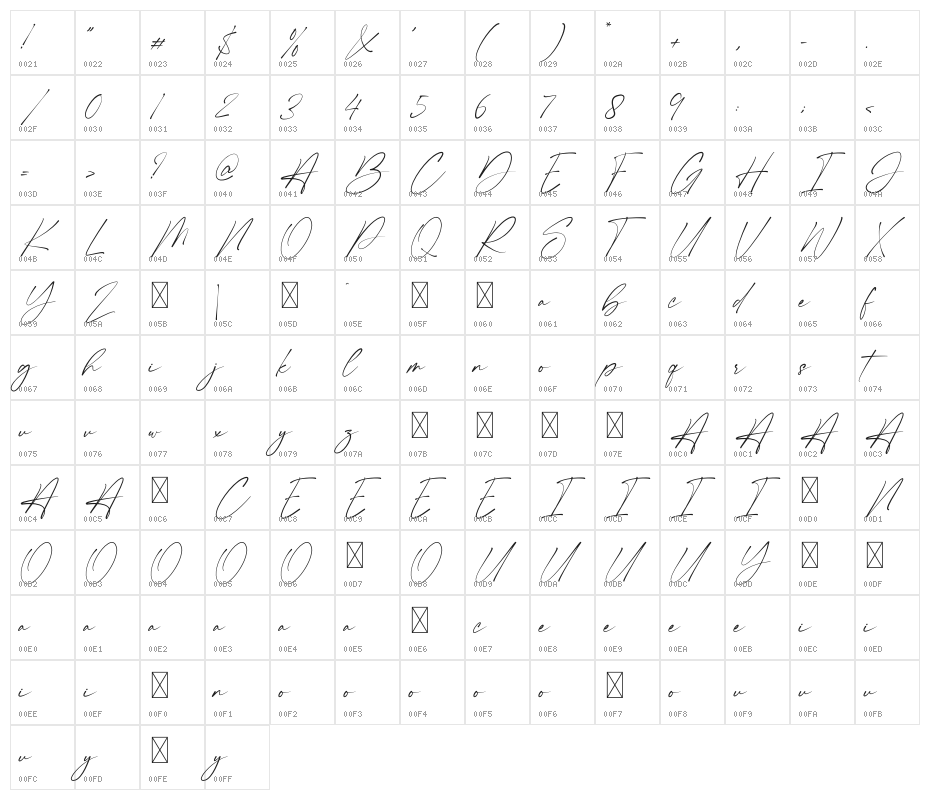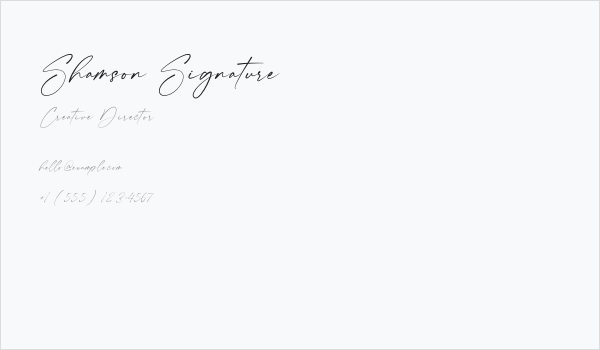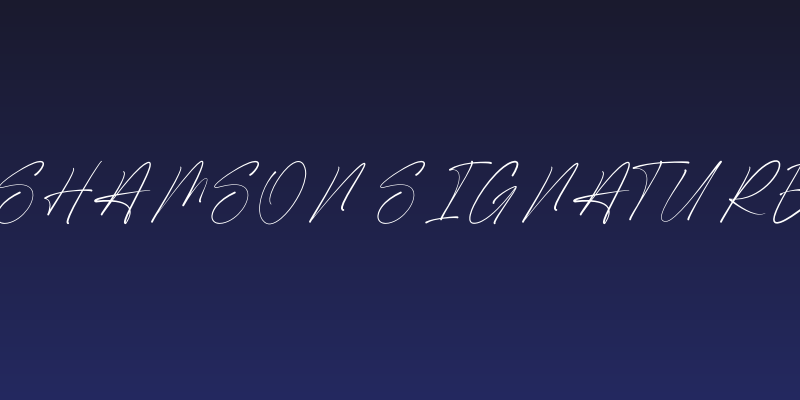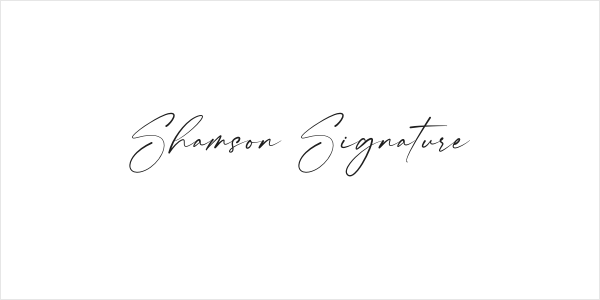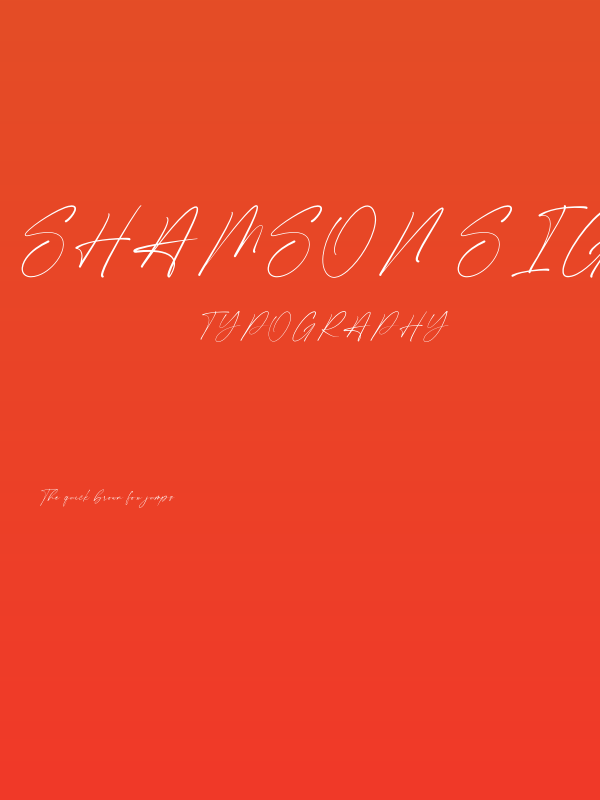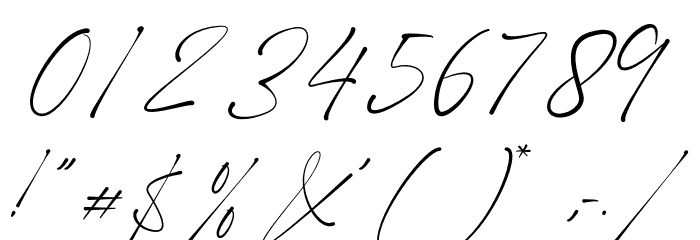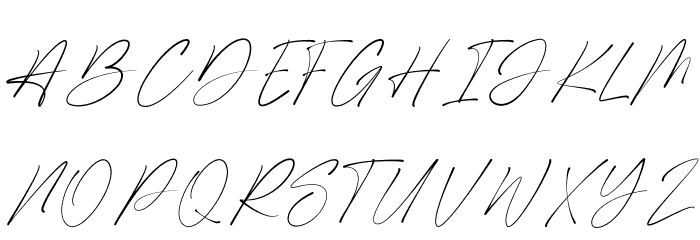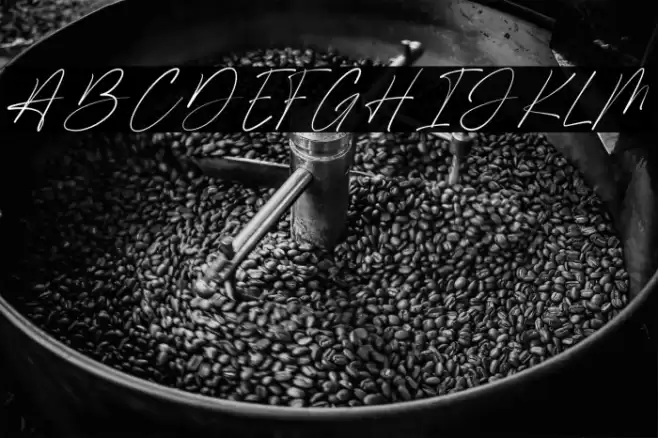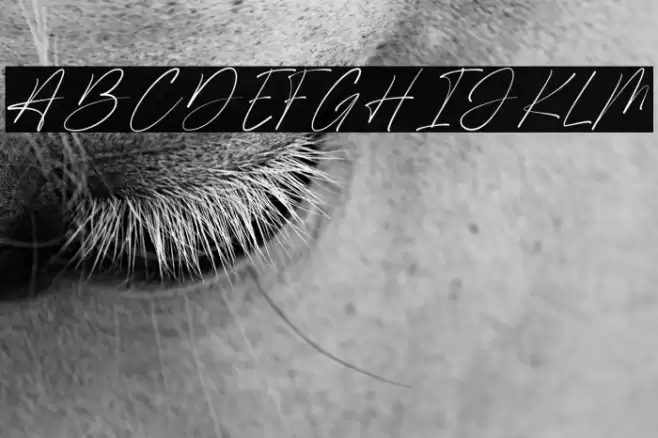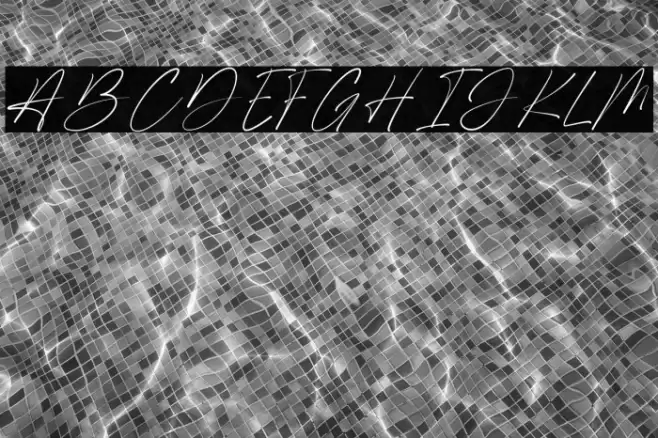
Shamson Signature Font
| Gesamtstil | Elegant, Sophisticated |
| Anwendungsfall | Logos, Invitations, Personal Branding |
| Vorgeschlagene Projekte | Ideal for wedding invitations, personal branding, elegant logos, and high-end product packaging. |